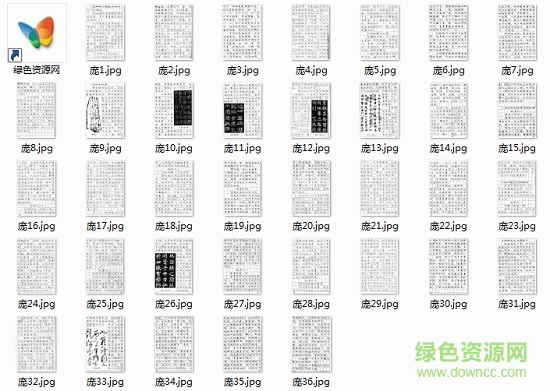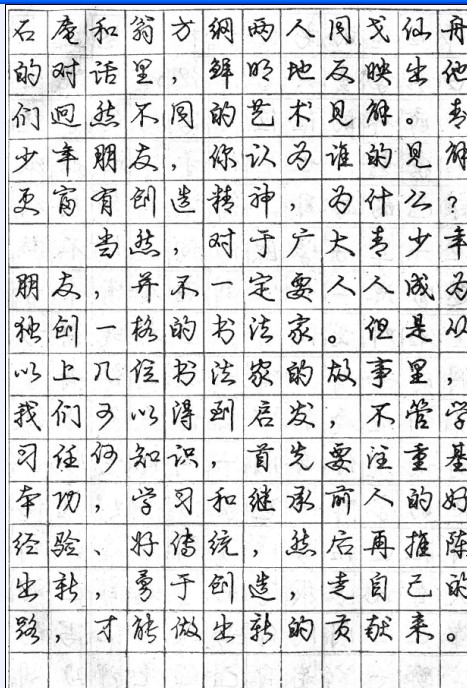
龐中華,著名書法家、教育家和詩人,四川達州市人,生于1945年10月21日,1965年畢業(yè)于西南科技大學(xué)地質(zhì)勘探專業(yè)。當代中國硬筆書法事業(yè)的主要開拓者?,F(xiàn)任中國硬筆書法協(xié)會名譽主席,龐中華硬筆書法學(xué)院院長,曾當選為第八屆全國政協(xié)委員。龐中華練習(xí)硬筆書法幾十年,遍臨名帖,他認為對前輩的書法不能一味臨摹,失去自我,而應(yīng)該不斷創(chuàng)新,用他的話說就是“讀古帖寫現(xiàn)代字”。同時,龐中華曾追隨國學(xué)大師文懷沙學(xué)習(xí),與范曾、王立平、空林子、周逢俊等名家同為關(guān)門弟子,于詩歌創(chuàng)作也具備一定功底。目前兼任燕堂詩社常務(wù)理事。
字帖(zì tiè)是供學(xué)習(xí)書法的人臨摹的范本,多為名家墨跡的石刻拓本、木刻印本或影印本。字帖多為兒童識字練字是習(xí)字形時使用,有塑字體的作用。 字帖按字體劃分,可以分為楷書、草書、行書、隸書、篆書等字體。字帖來歷:古代著名的書法都被刻在石碑上,后人為了臨摹他們的書法就把石碑上的字用紙拓下來,然后臨摹書寫。
記得上學(xué)的時候,還是初中高中,最喜歡買龐中華的字帖回去練字,龐中華的鋼筆字,特別是他的行書,行如流水,書寫簡便,哈,為了寫的一筆好字泡妞很好哦。